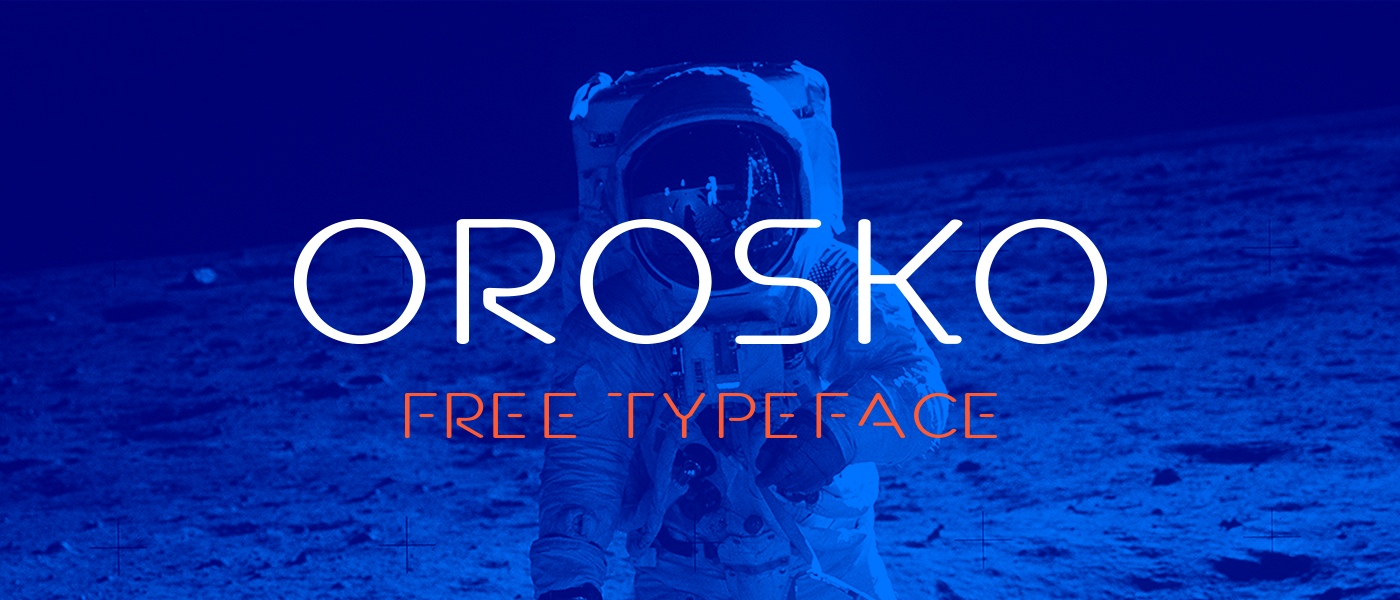
A fonte ‘Orosko Typeface’ é uma escolha inovadora para qualquer projeto onde desejas chamar atenção com elegância e simplicidade. Desenhada pelo designer francês Hamilton de AsbeenDesign, a Orosko traz um toque único que transforma o texto em um elemento poderoso para logos, cartazes, anúncios e muito mais. Perfeita tanto para uso corporativo como para criações digitais, ela atende desde os cards de visita até os livros, passando pelas embalagens e até mesmo os panfletos. Com a sua sem serif elegante, a Orosko é uma excelente adição para qualquer projeto que busque estética clara e confiável, tornando-a um recurso indispensável para designers em busca de uma fonte versátil.